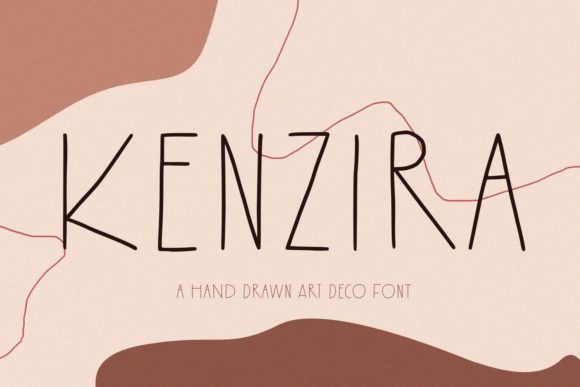
Kenzira
適切なデザイン要素を見つけるのは難しい場合がありますが、Kenziraは作品を即座に引き立てる優れたコレクションを提供します。
精密に作られたKenziraは、クリーンなベクター、滑らかなタイポグラフィ、そして安心のための商用ライセンスを提供します。
POD(オンデマンド印刷)製品、結婚式の招待状、またはソーシャルメディアのグラフィックを作成している場合でも、Kenziraは理想的です。